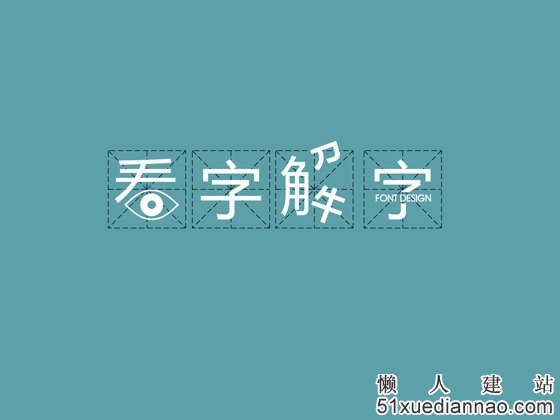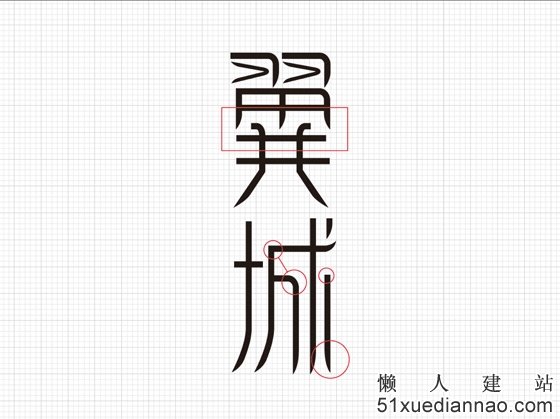
由太极来讲中文字体设计技巧及经验
心法
既然是武功秘籍 肯定有内功心法 那我们就先从内功开始练起
两仪
大家对太极图肯定都很熟悉了 阴阳阴阳 有阴必有阳 这是太极的两仪
也就是说凡事都有两面 做设计也一样 在同一个命题下 一个设计方向的背后肯定还有另外一个完全不同的设计方向
四象
我们先来看这个由太极演化而来的工具
我把字体设计归为4个要素:
框架--自由
个性--识别性
我先解释下这4个要素
框架:大家都知道 汉字 俗称方块字 这个方块呢也就是框架了
自由:这个自由是相对框架而言 也就是不受方块约束的字体(例如草书)
识别性:既然是字 那肯定要大家都能认识 有的字经过设计以后还能很方便的认出来 也有的字设计完后要经过一番思考才能认出来 这就是识别性的强和弱了
个性:这个也是相对识别性来说的 有的设计师为了强调某种个性 而牺牲掉识别性 例如:涂鸦字体 以前街头给人画龙字啊凤字的师傅就是个性字体设计高手
他们之间是相对的 (现在你看不懂没关系,继续看下去你就明白了)
这个工具有啥用呢?
我们再看 由四象推算出来的八卦 你可能会明白一点了
我们先看篆书,位于这个坐标工具左上角 也就是框架和个性的极限交汇点上
先看形态 很明显篆书是严格的在方块进行造型的 也就是以框架为基础来设计的
由于篆书是象形字转化而来还没完全脱离象形字的构造 在我们今天看来这种字体充满了个性 但识别性就比较差了
楷书:形态:依然是框架结构 识别上非常容易 所以它处在这个坐标工具的右上角 相对的来说 个性就比较少了 四平八稳
草书: 形态:没有框架 随心而置 识别上比较困难(你找找历代书法看看 看你能完整的认出多少来)但个性就非常强烈了 看的多的话 你不用看落款你就知道这是那个书法家的作品
行书:形态:没有框架 识别上较容易 个性和识别性兼备
这个坐标工具我主要用做分析别人字体设计的工具和作为自己设计字体时候的指南
说了这么多 你会用这个工具了么?还不会?!!!! 没关系 ~~我继续讲解
框架式字体设计
下面我先讲框架式字体的方法
从坐标工具来看 框架式字体设计 位于坐标工具的上半部分
在造字之前呢 我们先用坐标工具分析下这类字体的特点
请仔细观察下面这些字体!!!--形态?个性在那里?识别性强?弱?
这类型的字体 结构方正 个性鲜明 识别性较强 放在坐标工具上来分析的话 他们都处于白色圆圈这个范围内(你能将上图每个字体在坐标工具上不同的位置都标示出来么?)
下面这个是我为一个房产项目所做的一个字体设计 请注意:形态?个性在那里?识别性强?弱?
这个字体的特点:方正 很正统的框架式字体设计 字体重心全部上移 左方右圆 落脚呈尖刀状
why???????????????这个字体为什么设计成这样????????????????
接着看
这个字体设计的概念很简单:飞跃平凡的生活
飞跃-怎么用字体来体现飞跃呢?
A:我先从结构上下手:
1:把字体重心整体上移 造成向上的动感
2:拆除字体里的封闭结构(翼的田字)减轻字体本身的重量感 来强化整体向上飞跃的动感
B:从笔画上下手:
1:由于面对的客户男女都有 所以我选择左方右圆 这样就刚柔相济 比较中性
2:落笔融入羽毛的特点(落脚呈尖刀状) 贴近创意原点 并再度强化向上的飞跃感
框架式字体设计的基本方法
在开始做字体之前 我一般会先选择参考字体
为什么要找参考字体呢? 字库里的字都是专家多年研究和经过大众审美肯定的字体,有个巨人的肩膀让你站为什么不站呢?
字库里那么多字体 怎么选呢?选衬线体呢?还是无衬线体?(关于衬线体和无衬线体请查阅相关资料)
简单点来说
古朴 经典的个性 就选 衬线体
现代 简约 的个性就选 无衬线体来参照
选了参考字体参考什么????????????????
参考结构
这些基本的结构常识相信大家都知道
我讲一个框架式字体设计的秘诀:
没错! 顶天立地!
只有贴紧框架四边 整个字形才会显得饱满(写过pop的人都知道)
我们看下范例
在调整结构的同时 加入个性 和让笔画占据框架的4向
个性的塑造
在完成字体的基本结构后 我们现在来为字体加入个性
如前所叙 我就不多说了 看图
下图中的字体设计 你能说出设计师为什么要那么设计了么?他们是怎么为字体设计调整结构和加入个性的呢?它们各自的参考字体又是什么?
下图 是从参考字体 到 新的字体设计的一个流程图
我们现在 再重新来审视这个字体设计:
它还有没有结构上的缺陷?
它笔画粗细是否合理?
它空间分割是否美观?。。。。。。
下面是我做字体设计的另外一个秘诀:
下面我们再来看一个框架式字体设计的范例
这是我非常喜欢的一个字体设计
在4个要素点的把握上功力深厚
一般来说框架式字体设计做出来都多少有点死板 但上面这个设计师就敢于突破框架的束缚
这就是我想讲的 另外一个秘诀:
现在我们再返回来看看之前看过的这些字体设计
你现在看这些字体设计的眼光是否又不一样了呢?
关于个性
我们再看看这个范例
塑造个性的方式多种多样 不仅仅是字形
我就不多说了 留给大家自由发挥
下面即将进入本秘籍的核心部分!~!!!!!!!!!
绝招来了~!!!!!!!!
乾坤大挪移
乾坤大挪移 之 英文字体转化为中文字体设计
先看大师范例
陈大师 早已练的烂熟于胸了
乾坤大挪移 之 图形转化为中文字体设计
设计变形金刚这位仁兄的功夫也非常了得
乾坤大挪移 之 照片转化为中文字体设计
这个是我的拙作
练好以上3招 你就可以找 张大师 比划比划了
乾坤大挪移 之范例
在看下面这些范例之前 边看请边为它们在坐标工具上定位 如果一看到一个陌生的字体设计你就能将他们在坐标工具上准确的定位 那恭喜你 你练好心法了
作者从欧式图案中吸取精华来做的字体设计 强调的是个性 形态上为了加强识别型采取了框架式
下图是我从欧式图案中吸取精华来做的字体设计 强调的是识别性 个性较弱
再出一个题目
这个也是我做的一个字体练习作品
它又在坐标工具上的那个位置呢?
logo 到标准字
乾坤大挪移 一个简单的应用就是 vi 中的 中文标准字了
看范例 我就不多说了
太极两仪之自由式字体设计
讲到现在 大家因该对坐标工具都很熟悉了
一般来说 自由式字体设计 都处在坐标工具的下半部分 相对框架式字体来说 自由式的个性会更强一些
依照惯例 先看范例
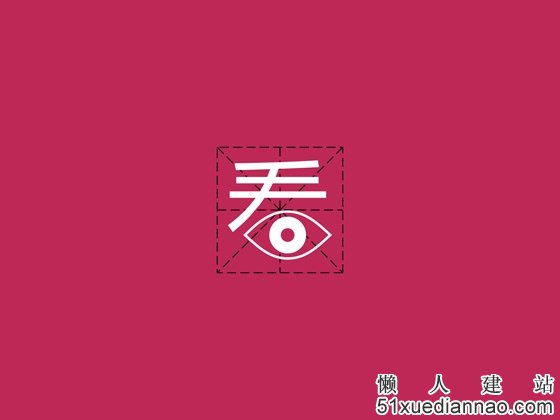
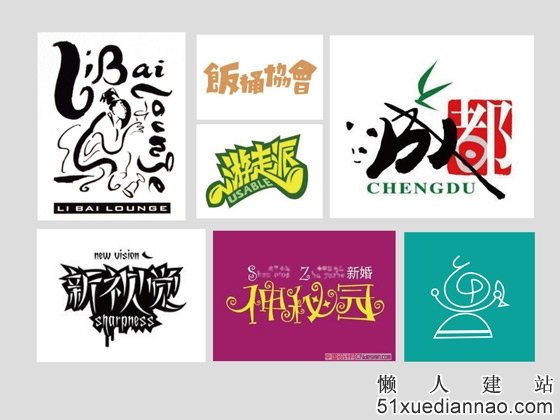
这些字体都有什么特点呢?
我们先看一个范例
这是我为一位朋友设计的个人签名
由于是属于个人使用的范畴 所以我强调的是个性
抛弃了框架 抛弃了大部分的结构 着重传达个人的特点
它处在坐标工具的什么位置呢?
关于自由式字体设计我只能找些参考来给大家分析 因为这个实在没办法解说 只能根据设计师的个性和项目的特性等来决定表现手法 二来表现手法千万种 都会影响字体设计的形态 就不一一解说了
经过前面的详解 相信大家都有各自的方法了
设计自由式字体的时候 最大的秘诀就是!!!!
太极之外 无极!!!
除了 框架式和自由式还有别的招式么???有!!
这一类的字体设计一般来说 处于坐标工具的中部 简而言之就是 带框架的自由式字体设计
先看范例
设计师:justmaoba
设计这类字体的秘诀就是:
终
大家可以下载这个坐标工具 随时备用 用来分析别人的字体设计和自己的指南
大家平时可以多做练习 吃饭的时候也可以练!
例如你喜欢吃香菇 那就用香菇的形态特质来做“香菇”2个字看看,你会做出什么东西来~~
或者 你在大便后仔细观察下你的大便 然后做个“大便”的字体设计玩玩,
总之 生活是无穷无尽的 设计也是无穷无尽的 掌握了此武功秘籍 就没有什么字体设计能难倒你了
和张无忌一样 你要的就是多看别人的表现形式和创意方法 用乾坤大挪移转为自己的功力了